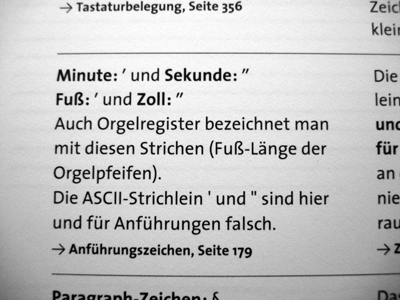
Zollzeichen ... again
Ich sehe gerade in der Detailtypographie von Forssmann/De Jong, dass das hier im Forum als -Zollzeichen- bezeichnete Ding -Doppel-Ascii-Strich- genannt wird. Leicht zu erkennender Unterschied: Ascii-Strich senkrecht, Zoll (bzw. Fuss-)zeichen schräggestellt.
Somit wäre das erste Bild hier eben KEIN Zollzeichen, sondern ein Doppel-Ascii-Strich: http://www.typografie.info/typowiki/index.php?title=Anführungszeichen
Kann man das so sagen? Bitte um Aufklärung. Danke!
Auf S. 188 werden die senkrechten ASCII-Strichlein für Zollangaben als falsch bezeichnet. Ich finde allerdings in der ASCII-Tabelle auf S. 356 keine Zollzeichen. Bin gerade selbst etwas verwirrt.
Bei mir steht da: Die kleinen, etwas schrägen Strichlein verwendet man nur für Zeit- und geografische Angaben sowie für Fuß und Zoll. Daneben: Fuß und Zoll: (...) die ASCII-Strichlein sind hier und für Anführungszeichen falsch.
Jetzt interessiert mich aber noch, welche ominösen Zollzeichen in der zweiten Auflage der Detailtypografie gemeint sind. Die Systemschriften unter OSX scheinen diese nämlich nicht zu beinhalten. Ich sehe nur die ASCII-Strichlein und Accents bzw. Doppel-Accents. Die Zollzeichen müssten irgendwo dazwischen liegen. Spezieller Mathematik-Expert-Font?
Als Referenz: Zweite Auflage der Detailtypografie, S. 188, Kap. Fuß und Zoll. Danke!
Das ist echt nicht ganz einfach:
Es gibt in Unicode einen einfachen, meist leicht geneigten Strich (auch ›Minutenzeichen‹ & im englischen ›prime‹ genannt): U+2032. Lässt sich in HTML als ′ oder ′ schreiben:
Das ganze verdoppelt ist U+2033 oder ›Sekundenzeichen‹; ″ oder ″
U+0022 ist das, was auf deutschen Tastaturen auf Shift-2 liegt. Umgangssprachlich ›Zollzeichen‹, laut Unicode aber ›Quotation mark‹. In HTML direkt einzugeben bzw. als " "
Sollte natürlich dennoch nie die typografisch korrekten (länderspezifischen) Anführungszeichen ersetzen!
Wozu ist dann ›Shift-2‹ überhaupt gut, möchte man fragen …
Nun ja, bekanntermaßen ist Computerschrift eine gewachsene Angelegenheit, bei der gerade am Anfang typografische Regeln (oder gar Finessen) außen vor bleiben mussten.
Die ›zwei geraden Strichlein‹ sind und bleiben Anführungen – nämlich für Computersprachen, wie z.B. eben HTML. Im typografischen Satz ist dieses Zeichen recht nutzlos.
Dass in vielen Fonts keine sichtbare Unterscheidung zwischen Zollzeichen und U+0022 gemacht wird, stellt einen kleinen Trost dar: Oftmals ist dieser Unterschied in der Praxis also hinfällig.